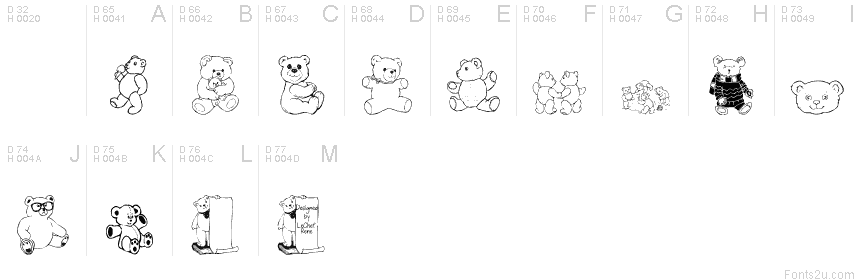
LCR Prestigious Teddies von Rene Miller ist eine kostenlose Dingbat-Schrift mit Bärenmotiven, die durch Cartoon-Konturen und abgerundete, plüschige Formen besticht. Die Bären teilen sich einen weichen, handgezeichneten Stil – vom stehenden Bären mit Schild bis hin zum sitzenden Bären in einfachen, spielzeugartigen Silhouetten.
LCR Prestigious Teddies eignet sich perfekt für Kinderzimmer-Papeterie, Einladungen zu Kindergeburtstagen, Geschenkanhänger, Scrapbooking, Sticker und verspielte Etiketten, überall dort, wo ein einzelnes Bärenmotiv als Dekoration dienen soll. Zudem passt die Schrift ideal zu Rändern, Eckverzierungen und thematischen Highlights, die einen freundlichen Teddy-Charakter statt formaler Symbole erfordern.